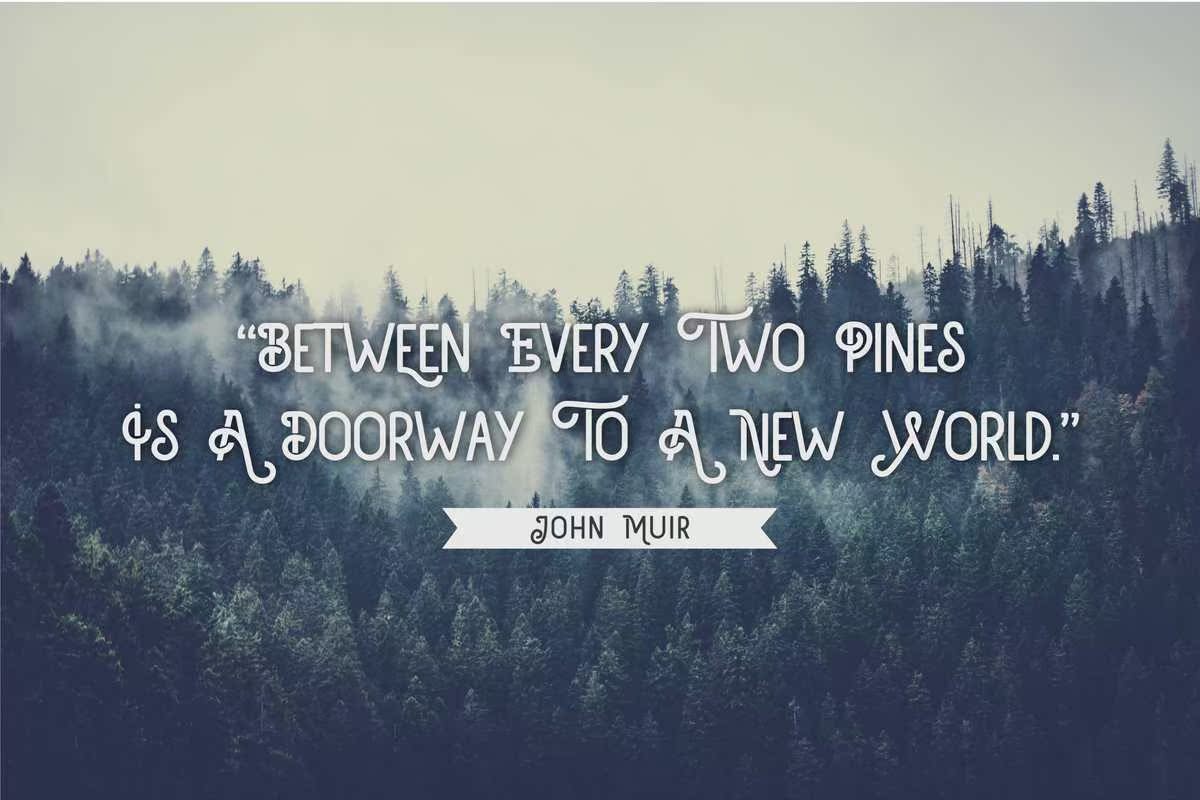
Galguna将优雅、极简主义和年份感结合起来,提供了一种对人眼不敏感的书写风格——无瑕无瑕的书写风格,吸引了人们对字体的观看。这种风格可以被许多人的日常欲望所迷惑;无论您是在重新制作名片、包装、徽标还是杂志。Galgunaw将为您提供新的创作机会。Galguna将优雅、极简主义和年份感结合在一起,提供一种对人眼有效的脚本风格——无瑕无瑕的写作风格,这对任何一个观看字体的人来说都是非常有吸引力的。它可以被许多人视为他们每天的愿望;无论您是在重新制作名片、包装、徽标还是杂志,Galguna都将为您提供新的机会。